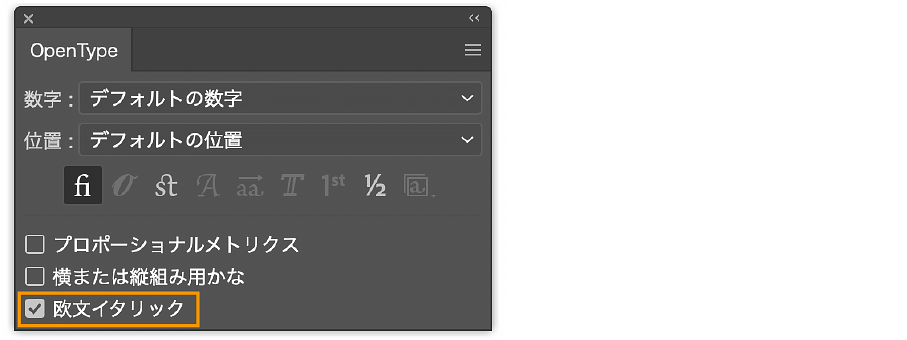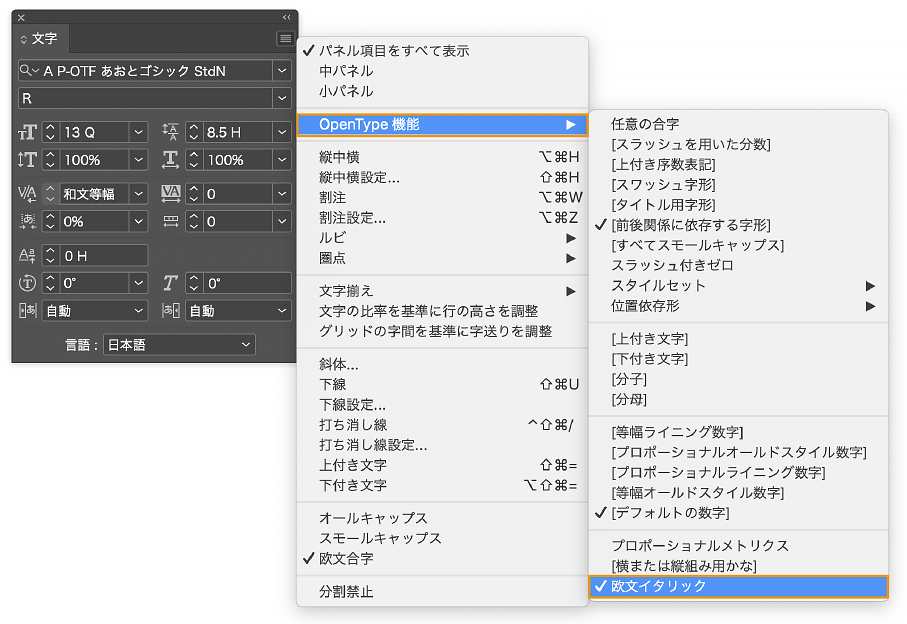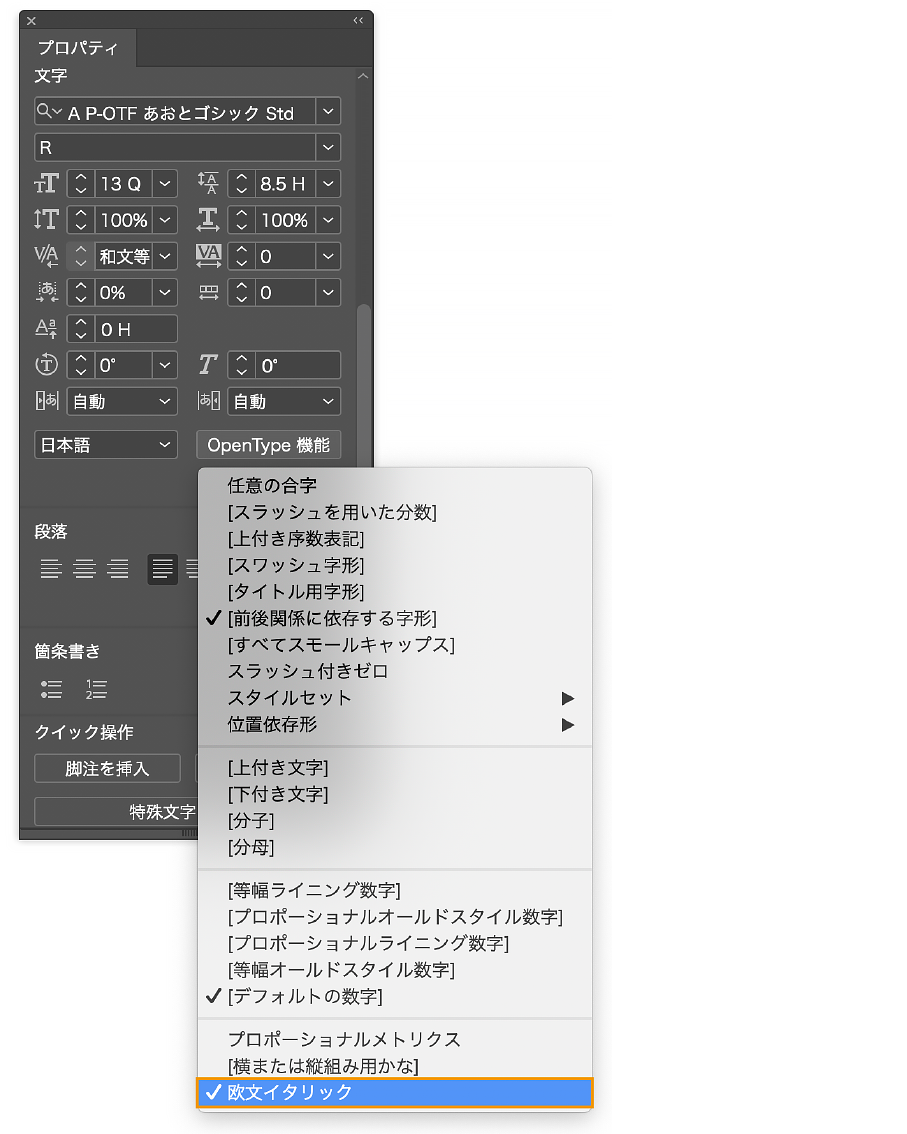
【あおとゴシックについて】
あおとゴシックの特徴
あおとゴシックはAdobe-Japan1-3に準拠しています。
加えて、デフォルトのプロポーショナル欧文に対応するイタリック体を搭載しています。
通常のAdobe-Japan1-3の書体では搭載しないイタリック体を搭載することで、
和欧混植の際の利便性を向上させた書体となっています。
イタリック体を呼び出すには
あおとゴシックに搭載されたイタリック体は、OpenType機能「イタリック」を使用して呼び出すことが可能です。